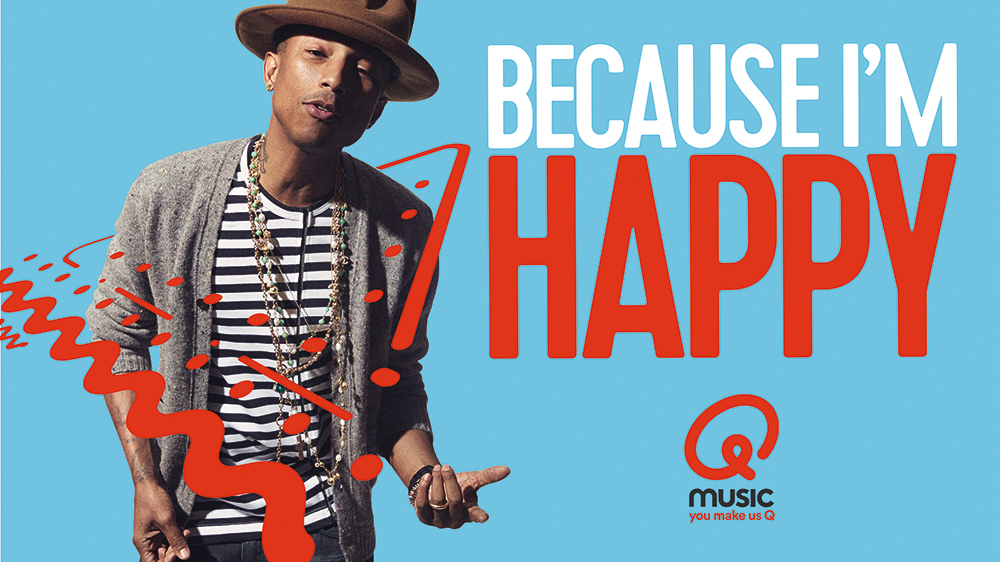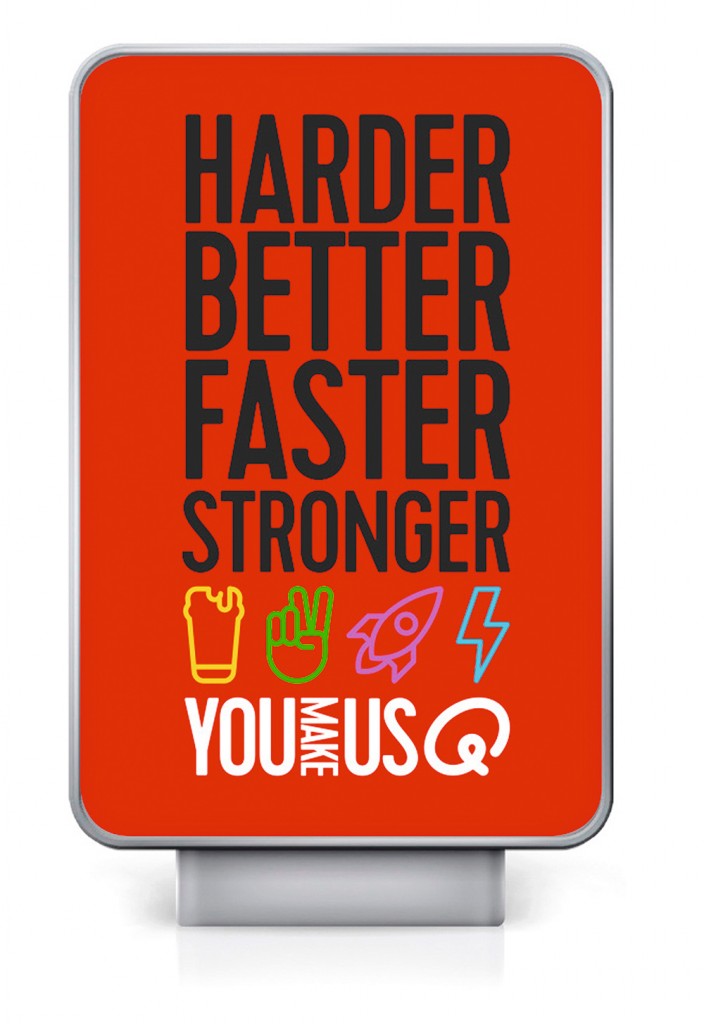
큐 뮤직 리브랜딩 사례 : 생에 대한 열의
벨기에와 네덜란드의 라디오 방송사인 큐 뮤직은 런던의 디자인 에이전시 딕슨박시에게 고루한 아이덴티티와 평판을 떨치고 싶다는 의견을 피력했다. 오늘날의 젊은 청취자들과 다시금 연결시켜 줄 응집력 강한 브랜드 위계를 바란다는 의뢰를 한 것이다.
큐 뮤직(Q Music) 리브랜딩 : 생에 대한 열의
목표 청취자의 삶에 대한 갈망, 낙관주의, 무언가의 일부가 되고 싶어 하는 욕망에 영감을 받은 딕슨박시는 통통 튀는 색상과 커다란 아이콘 서체를 사용함으로써 진행자와 아티스트를 브랜드의 중점으로 삼았다. 다른 제품들과 채널들을 위한 플랫폼 전체에서 작용하는 위계를 설정한 것이다.
“이러한 실행은 잘 알려진 큐 뮤직의 아이디어를 손동작 같은 몸짓으로 바꾸어 냅니다. 우리는 음악의 한 표현으로 맥박이 뛰는 개념에 매료되었습니다. 추상적인 것을 만들어 내는 소프트웨어를 통해 큐 뮤직을 감싸 안을 뿐 아니라 이로부터 발산하는 일련의 시각적 맥박을 디자인한 것이며 또 다른 시각적 훅에서는 재능을 표현하고자 했습니다.” 딕슨박시의 공동설립자 아포르바 박시(Aporva Baxi)가 설명한다.